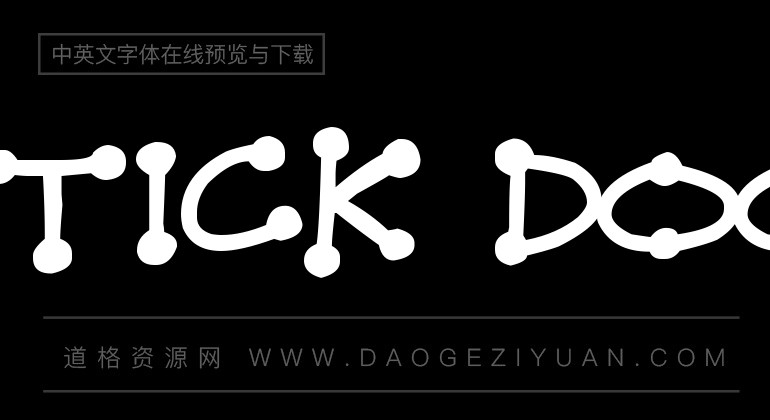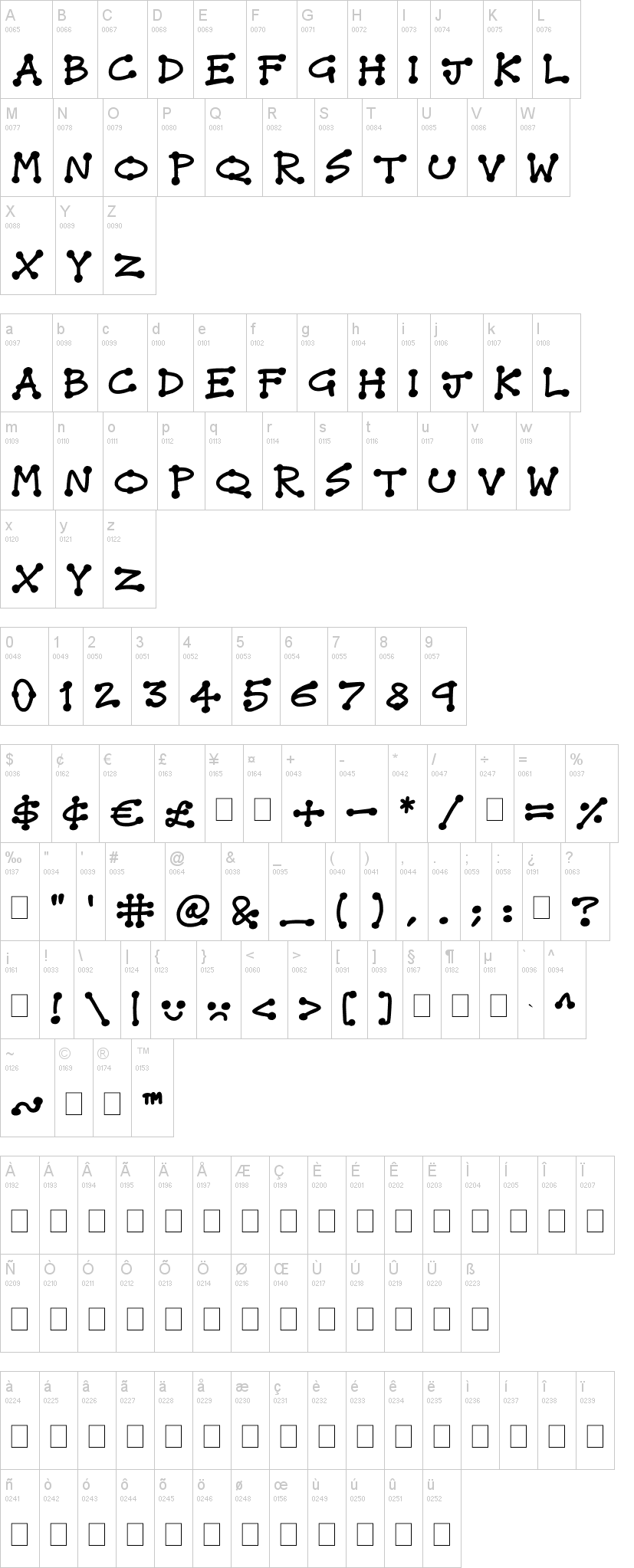
Dot Stick Doodles
Dot Stick Doodles 是一种特殊的手写字体,它的特点是字母和数字都由点和线构成,看起来像是小孩子画的涂鸦。这种字体非常适合用于儿童相关设计,例如儿童书籍、玩具包装和学习材料。这种字体的设计简单、可爱,给人以轻松、愉快的感觉,非常适合用于传达童趣和亲和力。Dot Stick Doodles 字体可以在商业和非商业项目中免费使用,可从多个字体网站进行下载。
Dot Stick Doodles是一款非常不错的手写艺术字体,具有很好的视觉感,适合于文化类的宣传设计、商业类品牌的广告和产品包装设计以及个性化文字排版等较多场景。
Dot Stick Doodles字符映射图